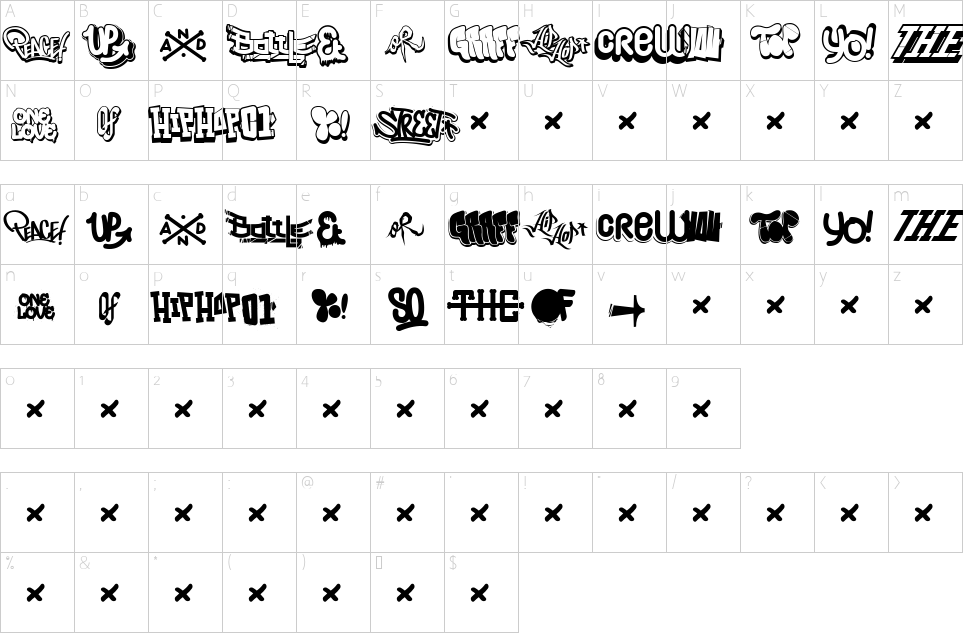
Hip Hop Lab Font – Download Grátis
Descubra a fonte ‘Hip Hop Lab’ para Windows e Mac. Essa fonte foi criada por Qkila e já foi baixada 183,840 vezes. Embora não possamos exibir características específicas da fonte aqui, é fácil notar o estilo único e dinâmico que a faz tão popular. A ‘Hip Hop Lab Font’ está disponível para quem busca estilos modernos e vibrantes para suas criações digitais. Ideal para designers de gráficos, designers de sites ou qualquer artista digital, a ‘Hip Hop Lab’ traz uma sensação de movimento e energia às suas obras. Se você está procurando por uma fonte vibrante e moderna, não pode perder a oportunidade de experimentar a ‘Hip Hop Lab Font’.